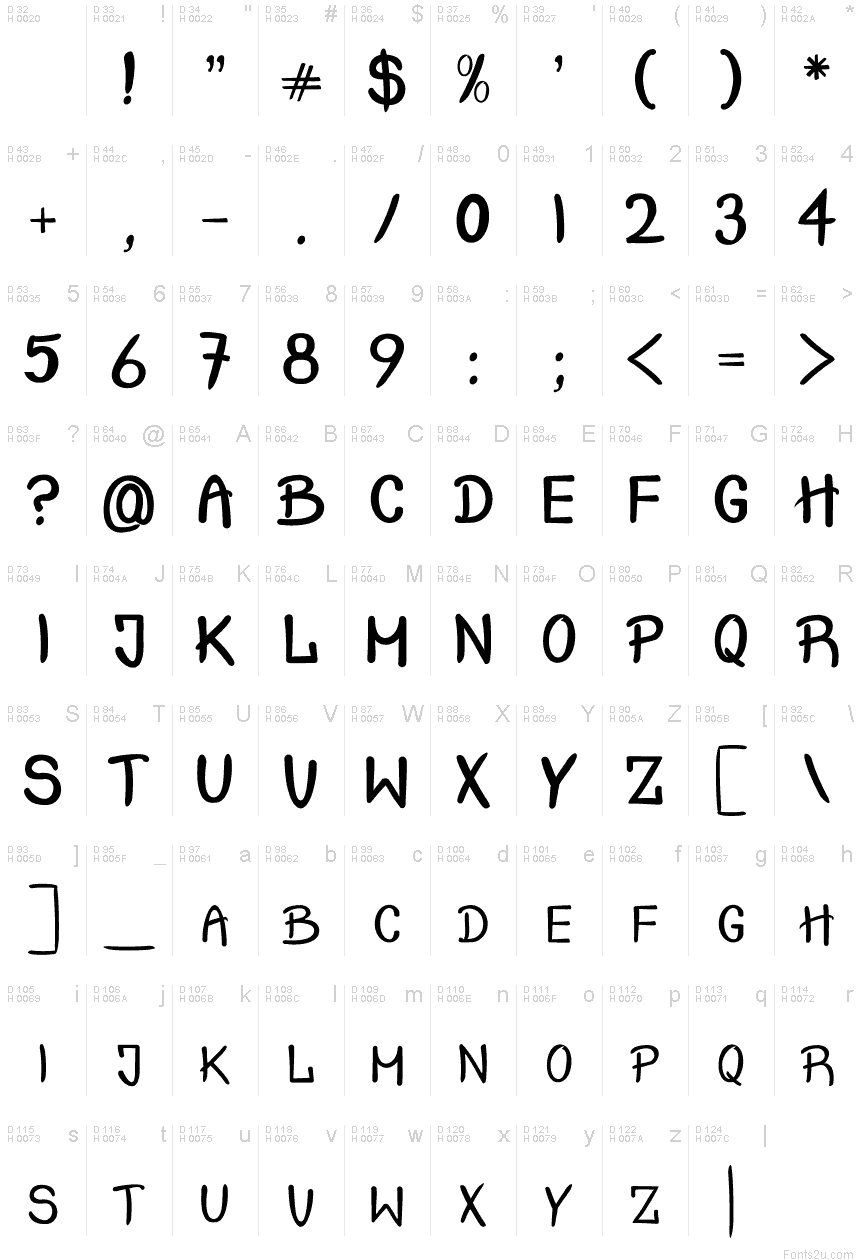
يُعد Crash Test خطاً جذاباً وجريئاً للعناوين (Display font)، يجسد جماليات القصص المصورة بوضوح. صممه Antrax، ويتميز بحروف ذات زوايا بارزة تضفي لمسة من الحيوية والمرح. وبفضل التباين في سماكة الخطوط والحواف غير المنتظمة، يمنح Crash Test شعوراً بالحركة والطاقة، مما يجعله خياراً مؤثراً للعناوين والشعارات وعناصر التصميم التي تهدف لجذب الانتباه. يجمع أسلوبه المتنوع المستوحى من القصص المصورة ببراعة بين الحداثة ولمسات الريترو، مما يجعله مناسباً لمجموعة واسعة من التطبيقات، بدءاً من التصاميم التحريرية ووصولاً إلى بضائع العلامات التجارية.
بفضل شخصيته القوية وتأثيره البصري الكبير، يعتبر Crash Test خطاً ممتازاً لمشاريع التصميم التي تهدف إلى إيصال روح المرح والإثارة والحيوية الشبابية.
خريطة محارف خط Crash Test